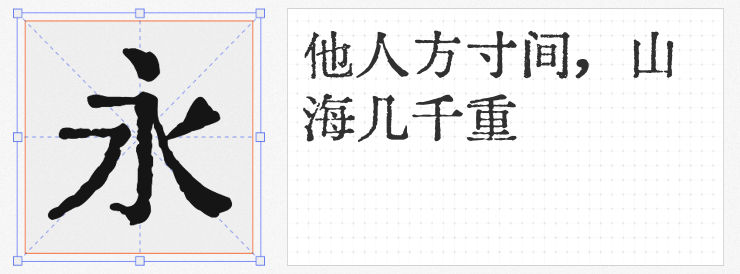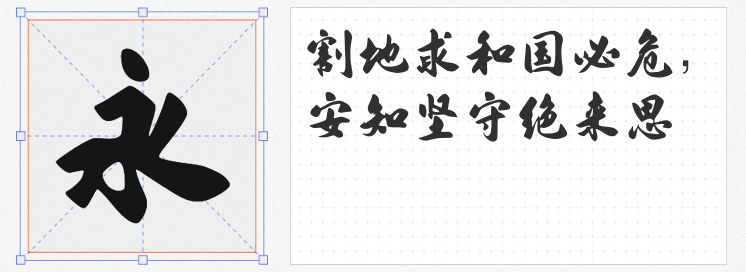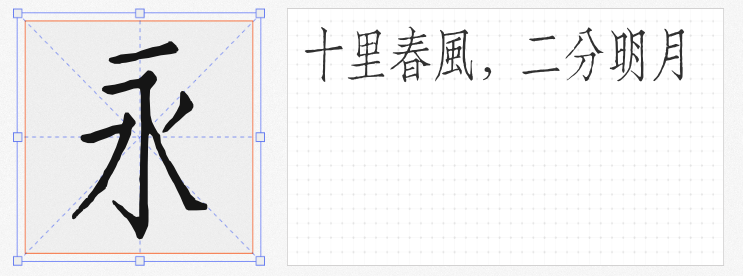
在国潮设计浪潮中,一款契合主题的字体往往能成为点睛之笔。本文精选四款兼具文化底蕴与现代审美的免费商用字体,助您轻松打造古风视觉盛宴。
1. 仲春仿宋
作为对聚珍仿宋二号长体铅活字的数字化复刻项目,仲春仿宋以扫描件提取技术还原了民国印刷字形的筋骨血肉。虽目前仍处于测试阶段,字形偶有残缺,但其清瘦挺拔的笔画与古朴的排版韵味,已显露出独特的年代质感。设计师可尝试将其用于古籍封面、传统节庆海报等场景,在留白处适当添加做旧纹理,更能凸显铅字印刷的岁月痕迹。
2. 纳米老宋
以汇文明朝为基底融合遍玨体特性的纳米老宋,通过边缘锯齿设计模拟出木版雕刻的肌理感。这种"不完美"的印刷效果恰与当下流行的残缺美学不谋而合,尤其适合表现传统戏曲、非遗文化等主题。建议搭配宣纸背景或朱砂印章元素,强化整体的历史厚重感。
3. 昆明海鸥体
叶根友团队历时两月打磨的这款创新字体,将红嘴鸥的优雅体态融入汉字结构。既有碑刻的苍劲古拙,又带现代书法的飘逸灵动,特别适用于文旅宣传、文创产品包装等领域。其独特的笔画弧度设计,在标题字排版时能自然形成视觉引导线,提升信息传达效率。
4. 字体家AI造字霸行
由AI神笔与叶根友字体联合开发的这款智能字体,在保留手写韵味的同时实现标准化输出。刚劲有力的笔画中暗含书法飞白,适合作为国潮品牌LOGO、短视频字幕等核心元素。开放免费商用政策更使其成为中小设计团队的性价比之选。
这四款字体各具特色,从铅字复刻到AI生成,从版刻模拟到自然拟态,共同构建起数字时代的国风字体矩阵。设计师可根据项目需求灵活组合,让传统文字焕发新生机。